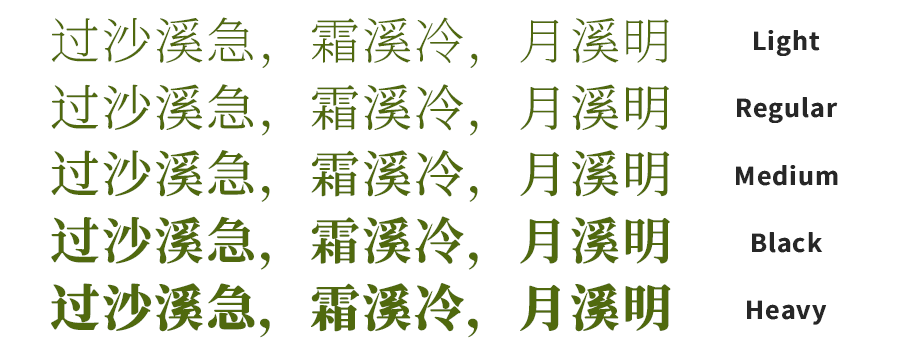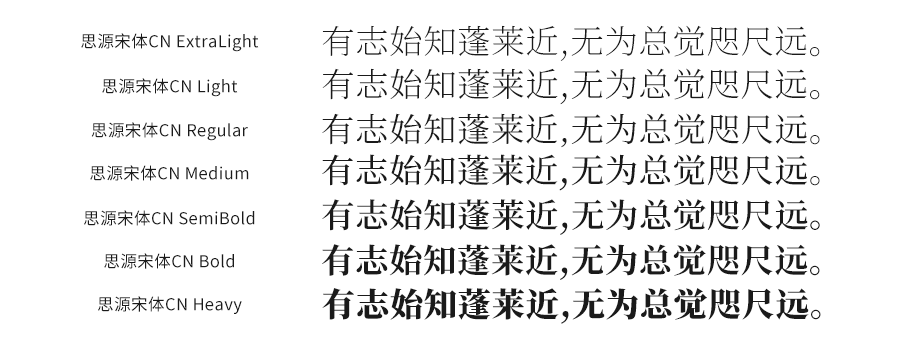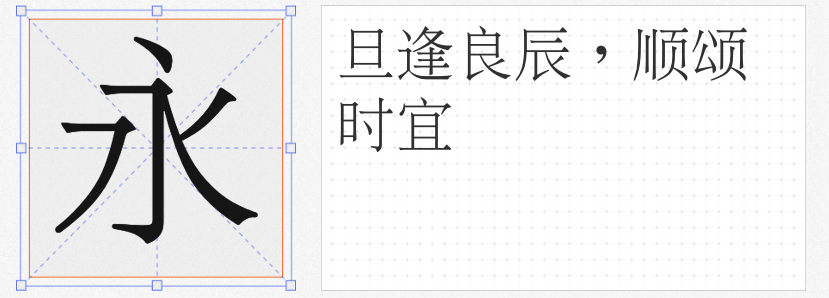
在设计领域,字体的选择至关重要,它不仅能传达信息,还能塑造整体的设计风格。今天,我们为大家推荐三款既实用又免费的商用宋体字体——“思源宋体 CN”、“寒蝉锦书宋”和“文鼎PL新宋”,它们将为你的设计作品增添独特的韵味。
1.思源宋体 CN
思源宋体 CN 是由 Adobe Type 发布的开源字体,与思源黑体相辅相成,共同构成了完整的字体家族。这款字体拥有7种粗细类型,每种都包含65,540个字形,确保了设计的一致性和美感。此外,它还支持拉丁语、希腊语和西里尔文字,让设计作品跨越语言界限,展现更广泛的文化包容性。
2.寒蝉锦书宋
寒蝉锦书宋是基于思源宋体进行修改的字体,通过添加圆角设计,使字体更加温润柔和。它在排版细节上进行了优化,重构了字重比例,使得字体粗细更加均衡,易于阅读。锦书之名寓意着锦上添花、前程似锦,这款字体将为你的设计作品带来美好的祝愿和视觉享受。它提供5种粗细选择,满足不同设计需求。
3.文鼎PL新宋
文鼎PL新宋是一款融合了上海宋和报宋风格的免费商用字体。它将两种宋体字体合并,以繁体优先处理重复部件,同时标点居中,呈现出独特的排版效果。这款字体随着1999年的授权衍生而来,具有深厚的历史底蕴和时代感。它适用于各种设计场景,无论是正式文件还是创意海报,都能展现出独特的韵味和气质。